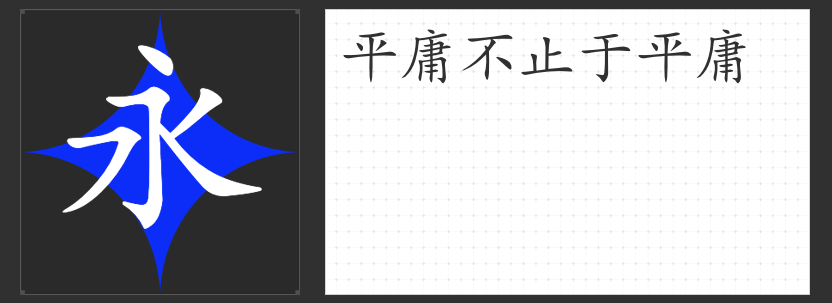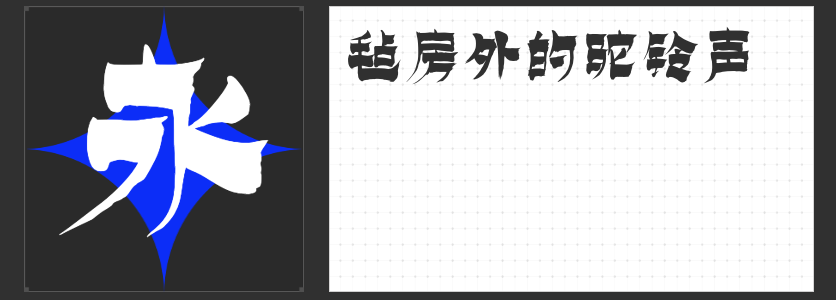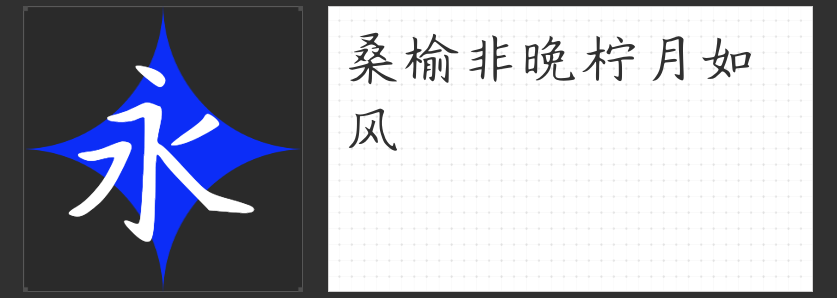
怀旧风情,设计中的复古字体推荐
在设计中,字体不仅是传递信息的媒介,更是营造氛围、塑造风格的重要元素。怀旧字体以其独特的韵味和质感,为设计作品增添了一份复古的风情。今天,将为大家推荐四款适用于设计中的怀旧字体。
1.云书法三行魏碑体
这款字体以魏碑为灵感,整体字形柔和流畅,颇具古风韵味。笔划严谨而朴厚灵动,风格朴拙险峻又不失舒畅流丽。无论是用于标题还是正文,云书法三行魏碑体都能展现出一种独特的复古美感,让设计作品更加引人入胜。
2.励字楷体简繁
励字楷体简繁以其圆润、娟秀、挺拔、整齐的笔画,展现了楷体的独特魅力。尖锋顿笔的运用,更是体现了楷体的精致与细腻。这款字体不仅适用于书写,更能在设计中营造出一种古典而优雅的氛围。无论是书籍封面、海报设计还是其他平面作品,励字楷体简繁都能成为点睛之笔。
这是一款极具创意的毛笔手书字体。笔画厚重而清晰从容,撇字有灵性,框架醒目,字型端庄。造字侠永刚漆书简繁以其独特的字体风格和统一的视觉效果,成为包装印刷、广告设计、平面设计等领域的优选。它能赋予作品一份古典与现代相结合的美感,让人过目难忘。
4.励字仿宋简繁
仿宋字体源自宋版书上的刻字风格,笔画粗细均匀,将楷书笔画和宋体字完美融合。励字仿宋简繁以其古朴的韵味和清晰的辨识度,成为设计中传递古典美感的理想选择。无论是用于书籍排版、标志设计还是其他创意领域,这款字体都能展现出一种独特的复古风情。
以上四款怀旧字体各具特色,无论是想要营造古典优雅的氛围,还是追求复古与现代相结合的美感,它们都能成为你设计中的得力助手。选择一款合适的怀旧字体,让你的作品更加独具匠心、引人入胜。